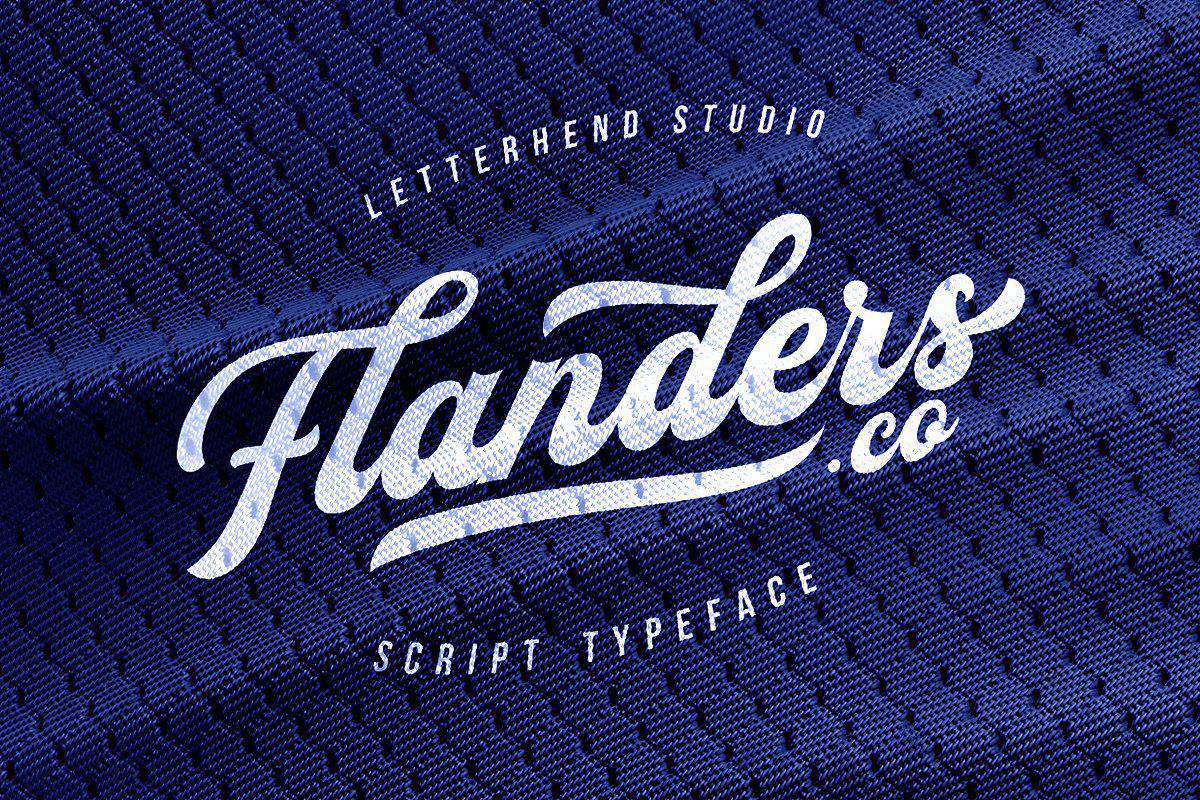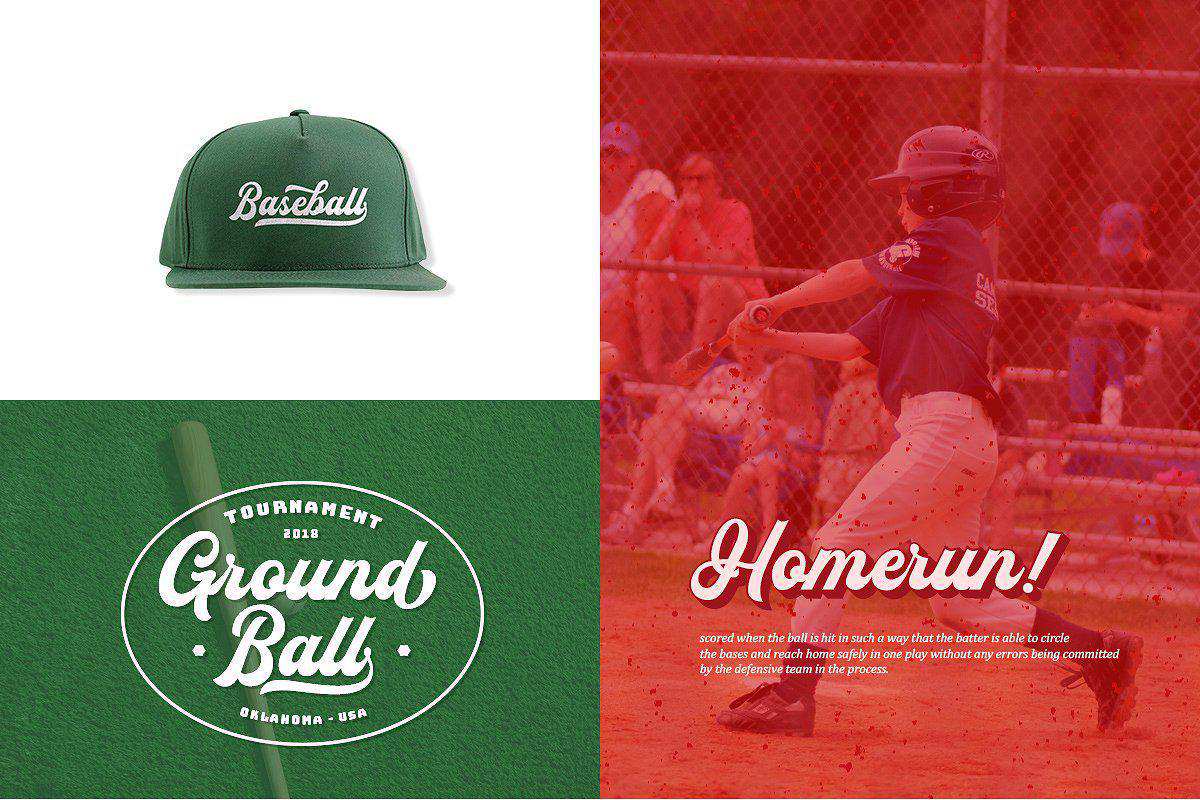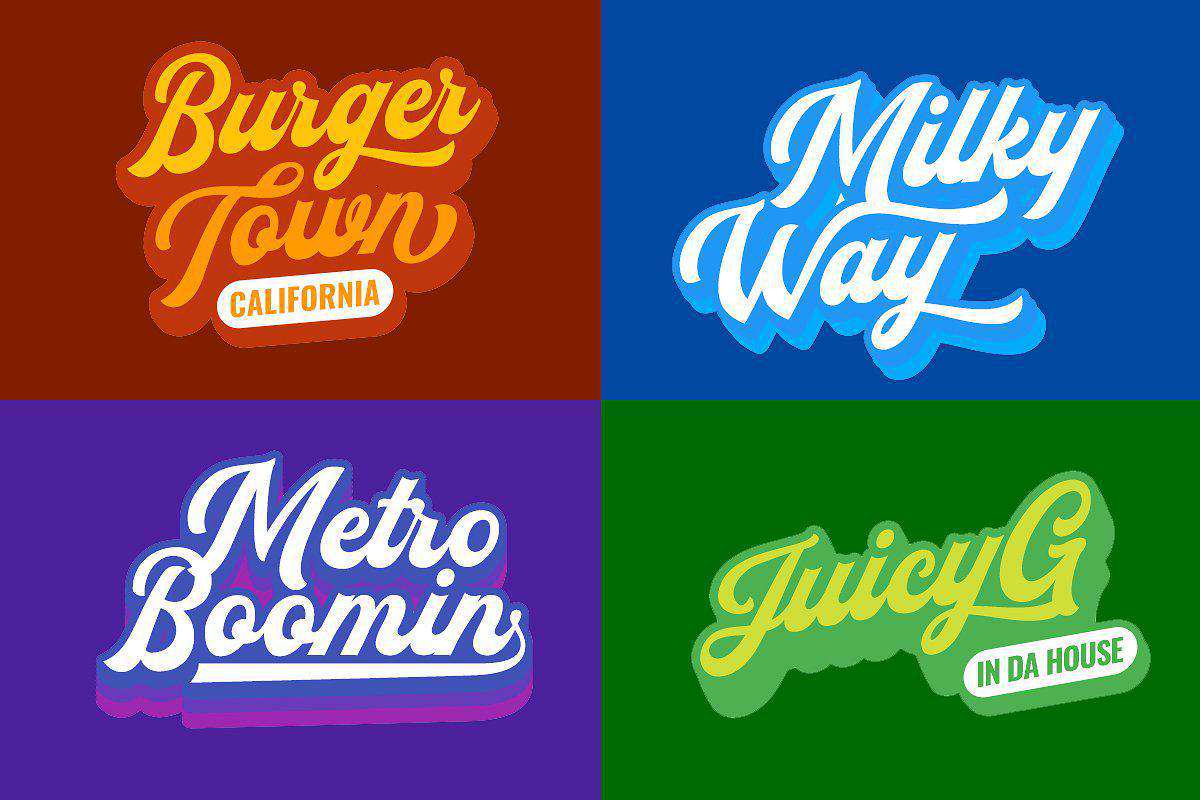
法兰德斯。ABOLD和ModernScript将满足Portytheme、logotype、quotes、wordmark等的超负荷设计需求。这有许多五种类型的功能,包括术语、文体替换、上下文替换、swash等,并支持多语言。法兰德斯。ABOLD和ModernScript将满足Portytheme、logotype、quotes、wordmark等的超负荷设计需求,这有许多五种类型的特点,如语言、文体交替、语境交替、浮华等,并支持多种语言。